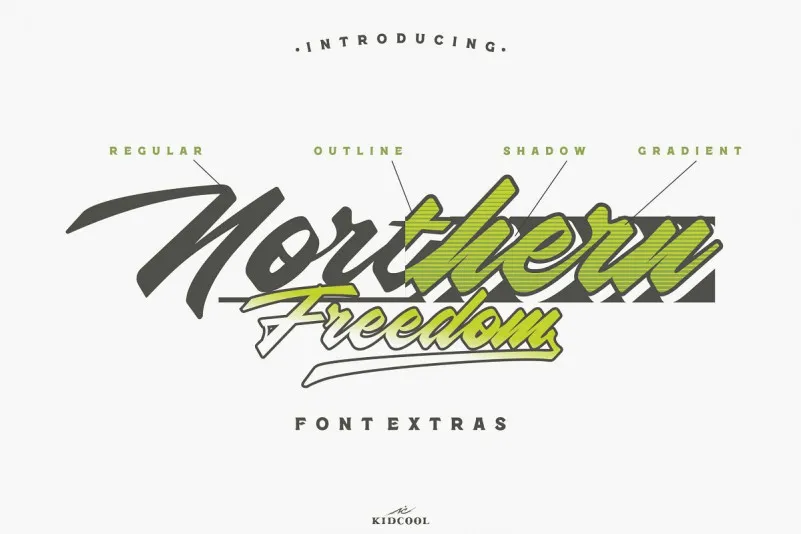
Northern Freedom Script Font – Fonte Grátis
Northern Freedom Script Font
Introduzimos a Northern Font – uma nova fonte de script moderna. Como designer, me orgulho de apresentar esta fonte ao grande público. Esta é uma proposta interessante para adicionar à coleção de vocês! Foi criada e compartilhada pelo KIDCOOL. A fonte “Northern Freedom” se destaca como uma opção moderna no catálogo de scripts digitais, ideal para quem deseja dar um toque especial às suas criações. Além da fonte principal, a Northern Freedom também oferece outras três variantes: shadow, gradient e outline. Essas adições permitirão que vocês possam criar múltiplas combinações, tornando ainda mais versátil essa escolha de fontes. Seja para projetos digitais ou impressos, esta fonte moderna é a opção perfeita para dar um toque único e original aos seus trabalhos. Para os amantes do design gráfico, este é um excelente investimento. Com Northern Freedom em sua coleção, você poderá criar uma paleta única de estilos que refletirão seu próprio estilo criativo.